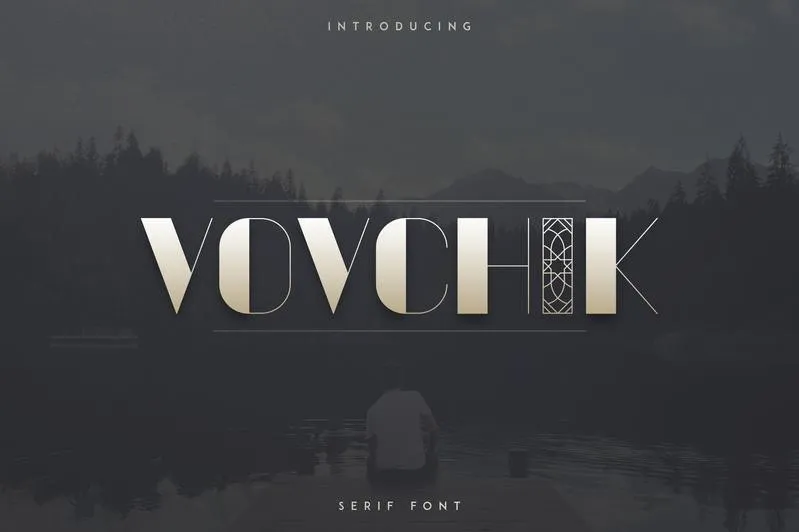
A fonte Vovchik Serfi é uma elegante escolha para qualquer projeto que busque um padrão atraente e sofisticado. Ela se destaca entre as serif fonts com seu traçado robusto e altamente detalhado, oferecendo 26 alternativas estilizadas para garantir diversidade na sua composição. Além disso, Vovchik Serfi conta com suporte multilingue, tornando-a perfeita para qualquer tipo de conteúdo que tenha uma variedade de idiomas a serem usados. Ideal tanto para grandes formatos quanto para detalhes mais finos e sutis, essa fonte oferece um alto grau de flexibilidade. Seja você criando materiais educacionais ou personalizando seu website com gráficos elaborados, Vovchik Serfi é uma escolha confiável e versátil que ajudará a destacar o conteúdo em sua página. Sujeitado ao designer vp_creative_shop, essa fonte representa tanto qualidade quanto criatividade no design.